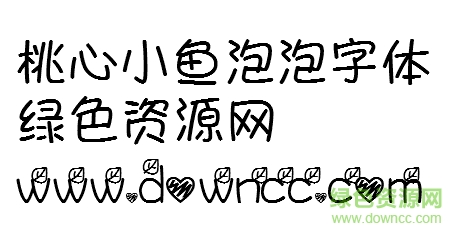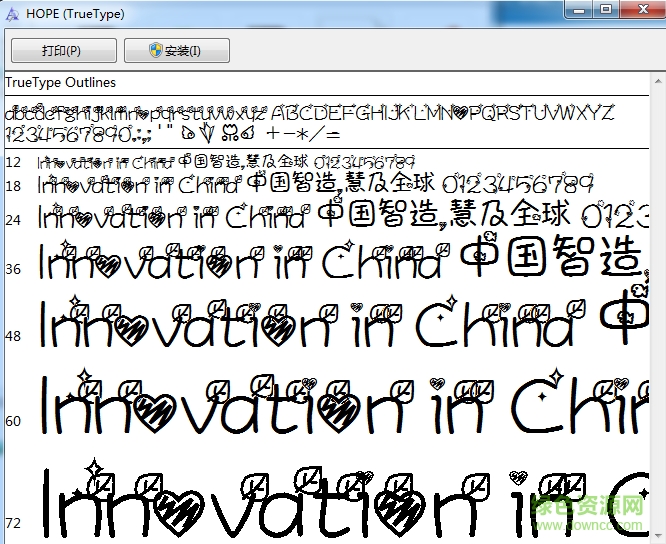
小魚泡泡字體是一款有著有著可愛桃心、小魚、樹葉、泡泡等豐富裝飾的卡通字體,讓你的文字變得生動活潑起來,喜歡收集字體的朋友千萬不要錯過哦,來綠色資源網(wǎng)一起體驗吧!
小魚泡泡字體是款可愛的創(chuàng)意中文字體,在字體字形中融入了多種圖形元素,趣味十足,可用于廣告設(shè)計、網(wǎng)頁設(shè)計、包裝設(shè)計、屏幕顯示等等場合,一定讓你的文字大有增益!